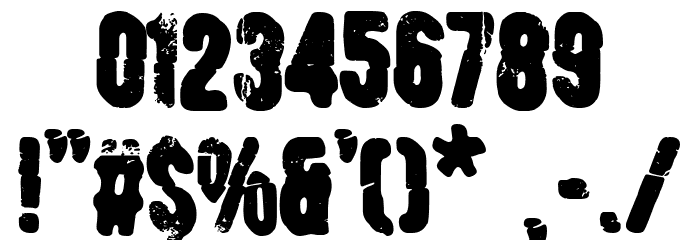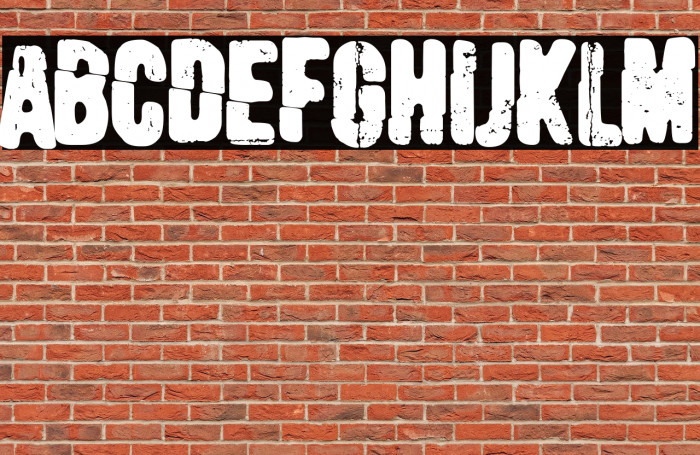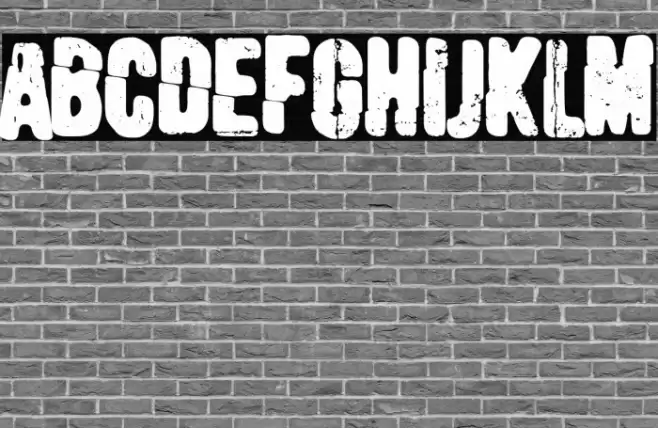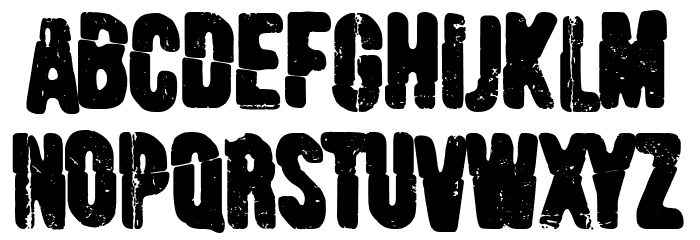
La Costa Dorada is Spain Font
✎ Messy
| Projetos propostos | Ideal for vintage-themed posters, album covers, branding for rustic or industrial products, and any design needing a bold, nostalgic touch. |